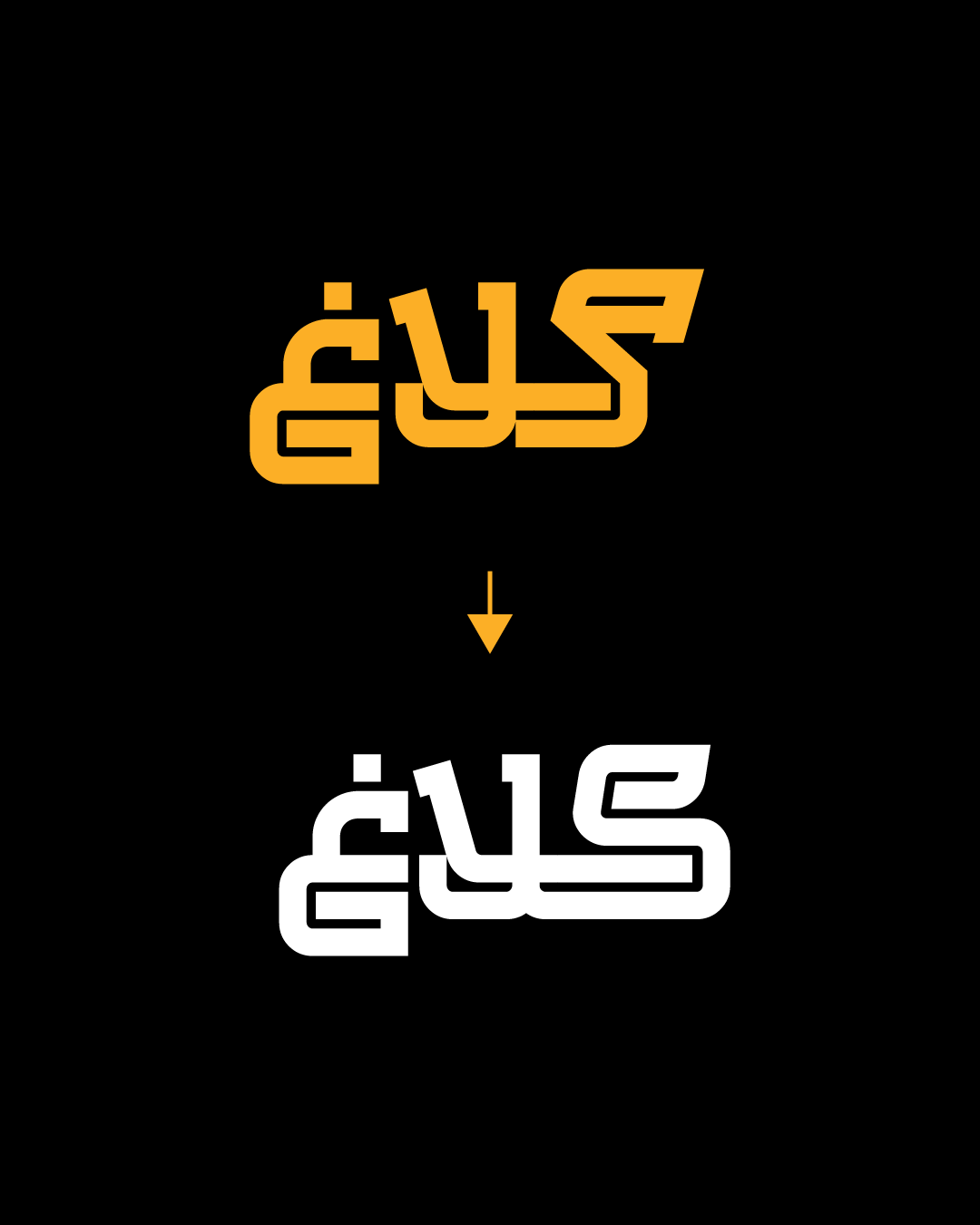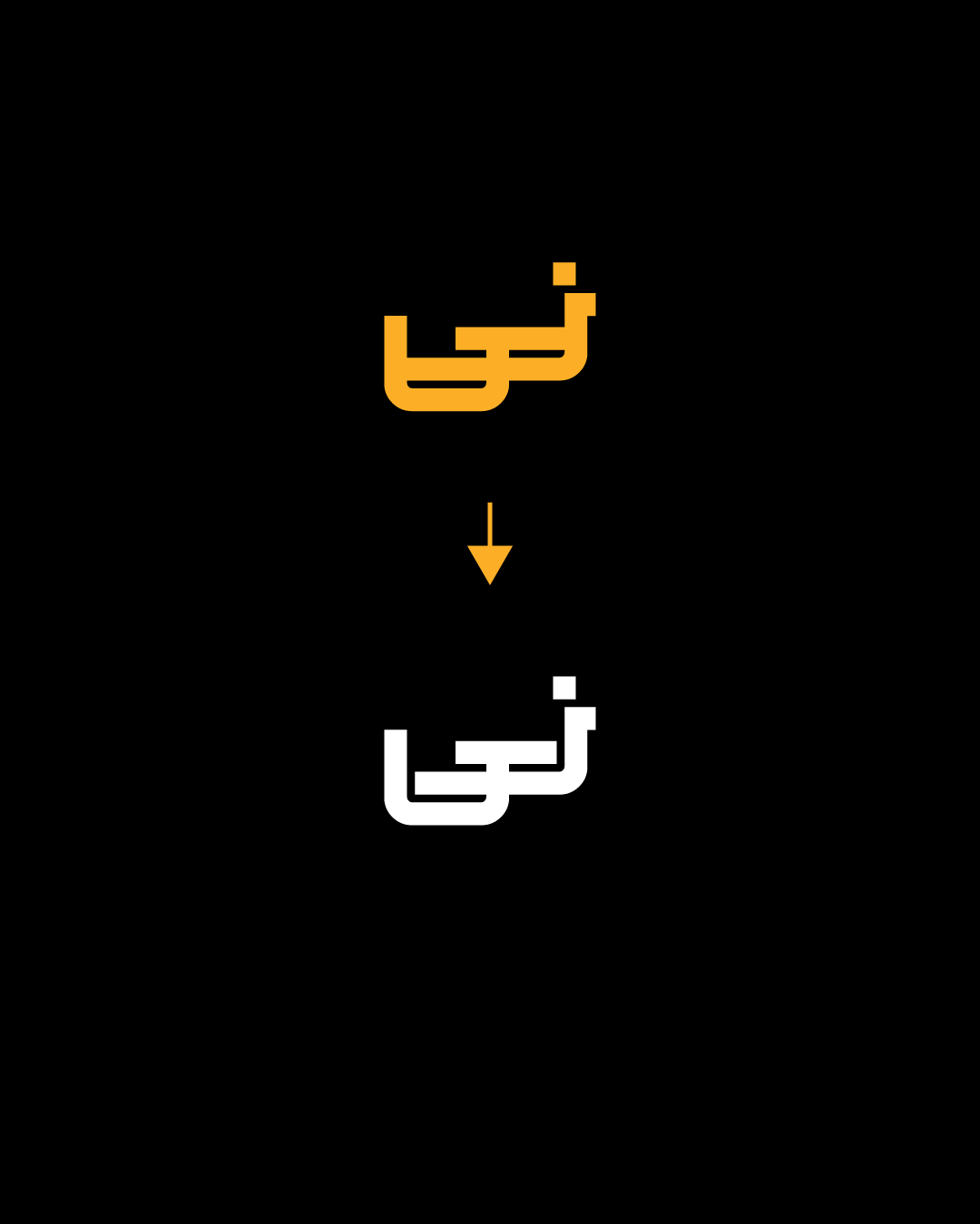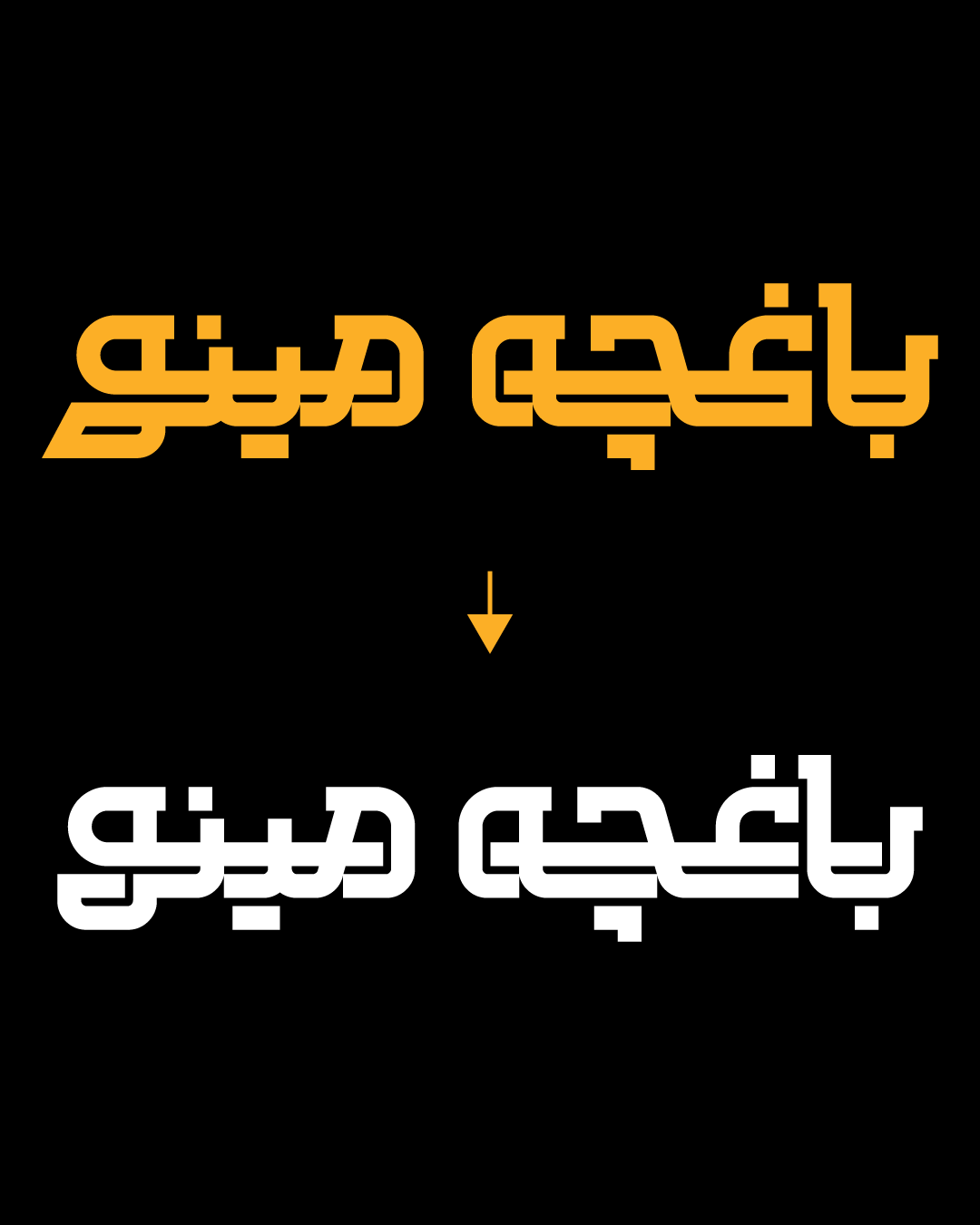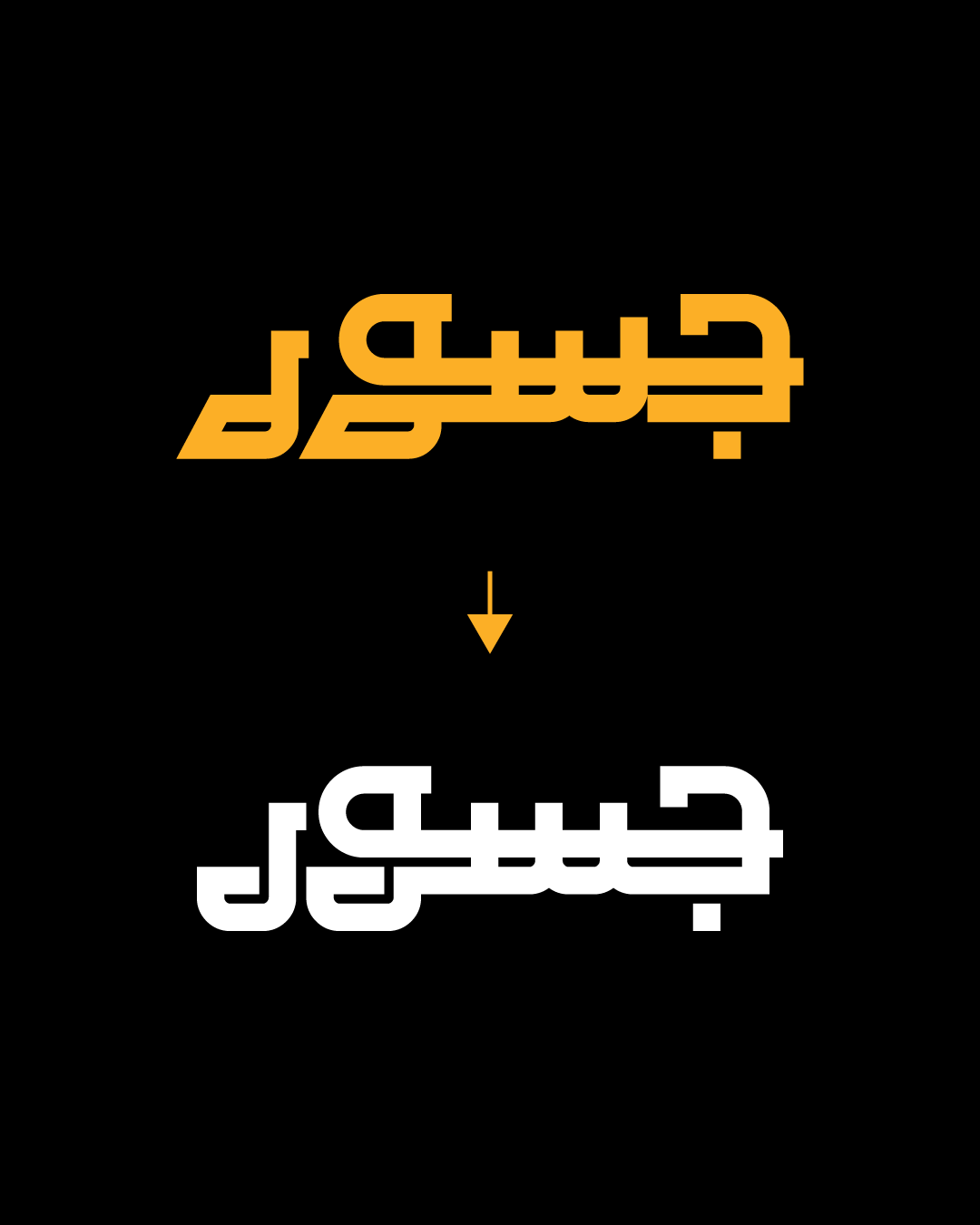
در نسخه‌ی ۲ فونت تکنو چه تغییراتی می‌بینیم؟
1. هماهنگ سازی سرکش کاف با ریتم و ساختار کلی حروفدر نسخه‌ی ۲ فونت تکنو چه تغییراتی می‌بینیم؟
2. هماهنگ سازی سرکش گاف با ریتم و ساختار کلی حروف
3. اصلاح پاشنه‌ی واو-ر بر پایه ریتم سرکش و فرم کاسه‌ نون
4.ایجاد انفصال در آغاز حروف init و تکرار همان انفصال در انتهای حروف fina از سمت چپ